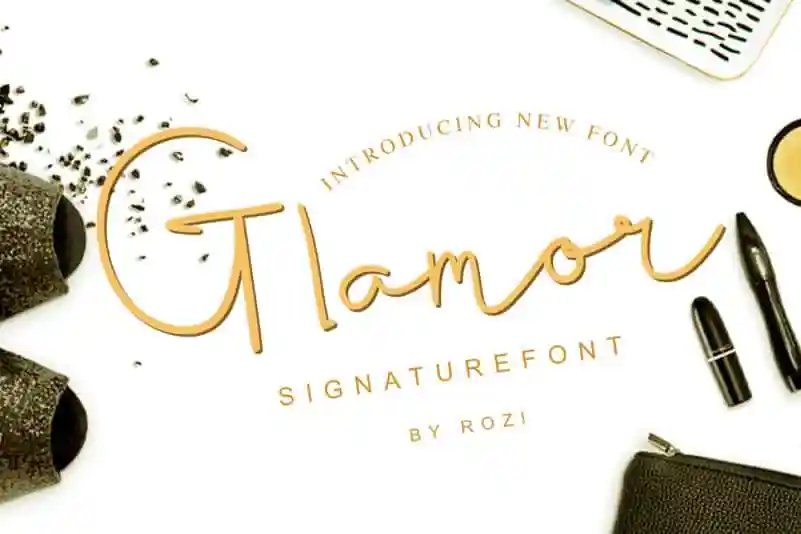
Glamour Signature Font é uma elegante escolha para aqueles que buscam personalidade em seu design. Com linhas finas e elegantes, ela se destaca perfeitamente para projetos como marcações, cabeçalhos, designs de casamentos, convites, assinaturas, logotipos, etiquetas e muito mais. Suas formas sutis e detalhes suaves conferem a Glamour Signature Font um ar de sofisticação que se assemelha à era dos anos 40 ou 50, fazendo-a ideal para criações em tons de cinza, preto e branco. Esse é o tipo certo para dar ao seu design um toque de glamour e elegância sem perder a sua personalidade única. Com Glamour Signature Font, você pode transformar qualquer projeto em uma verdadeira obra-prima.